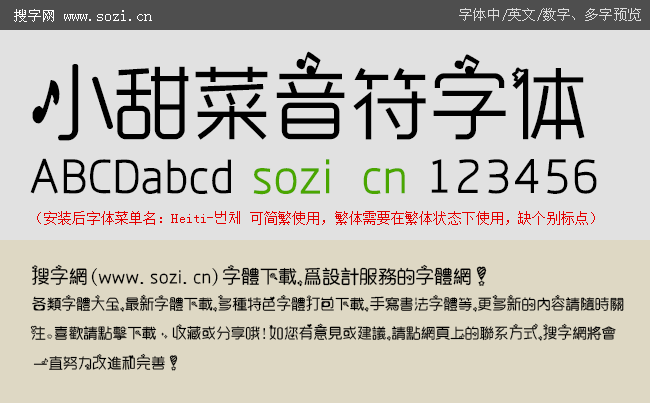
小甜菜音符字體
搜字網(wǎng)給大家提供一款小甜菜音符字體手機(jī)中文字體下載。這款手機(jī)字體是將黑體字體進(jìn)行重新設(shè)計,更加具有藝術(shù)感,字體間又嵌入了了漂亮的音符圖案。是一款非常藝術(shù)的字體,特別適合喜歡手機(jī)字體個性一些的朋友在手機(jī)上安裝使用。